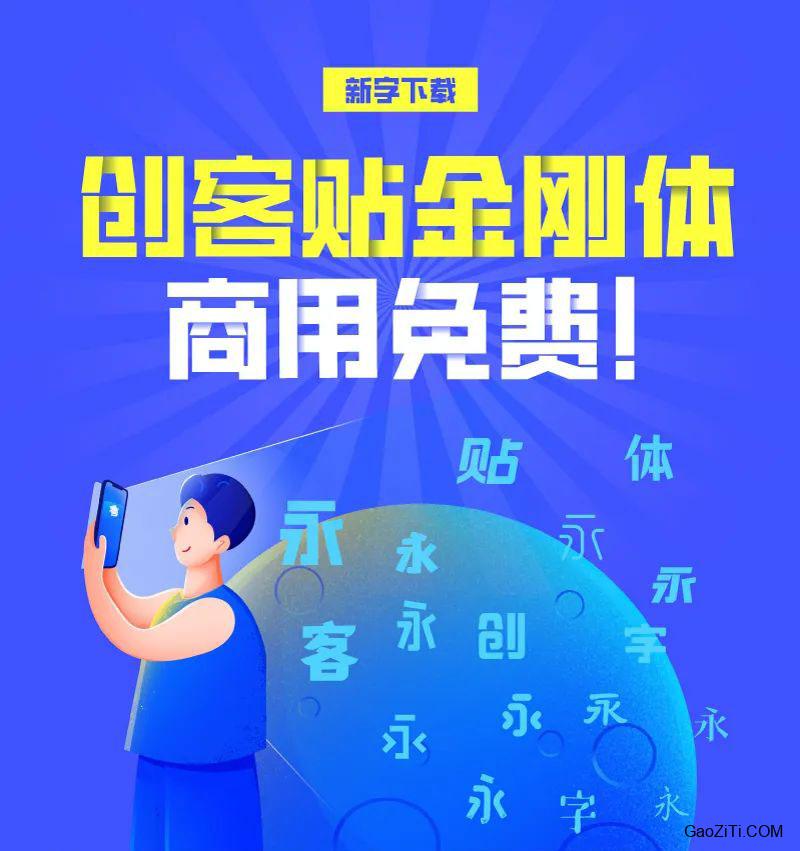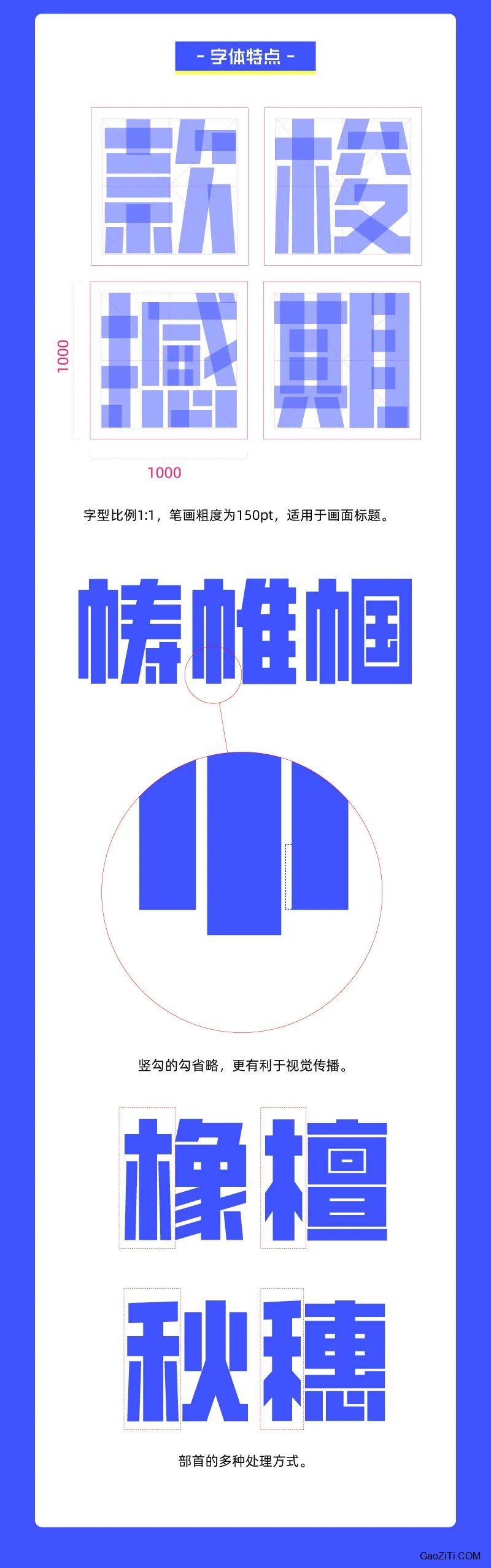
创客贴金刚体
为支援抗击疫情而创作的字体,将繁琐的笔画融合简化,简约有力量
创客贴金刚体是为支援抗击疫情而创作的字体,之前只在创客贴ckt.cn上架了这款字体,名称为“创客贴战疫体”。字体于2020年2月份上线,受到了用户的极大欢迎,我们也很高兴能够做出这么一点小小的贡献。现在我们将字体安装包开放下载,商用免费!
字体规格:简体中文,含西文及相关符号。基于中华人民共和国GB2312-80字符集标准,包含大陆简体汉字6763个、繁体中文16个、英文大小写52个,阿拉伯数字10个,以及682个符号,满足日常用字需求。
创客贴金刚体最初的设计理念是将一切繁琐的笔画融合简化,让字体更加简约有力量,而又不影响字体的识别性。适用于商业海报、电商banner、包装、品牌宣传。